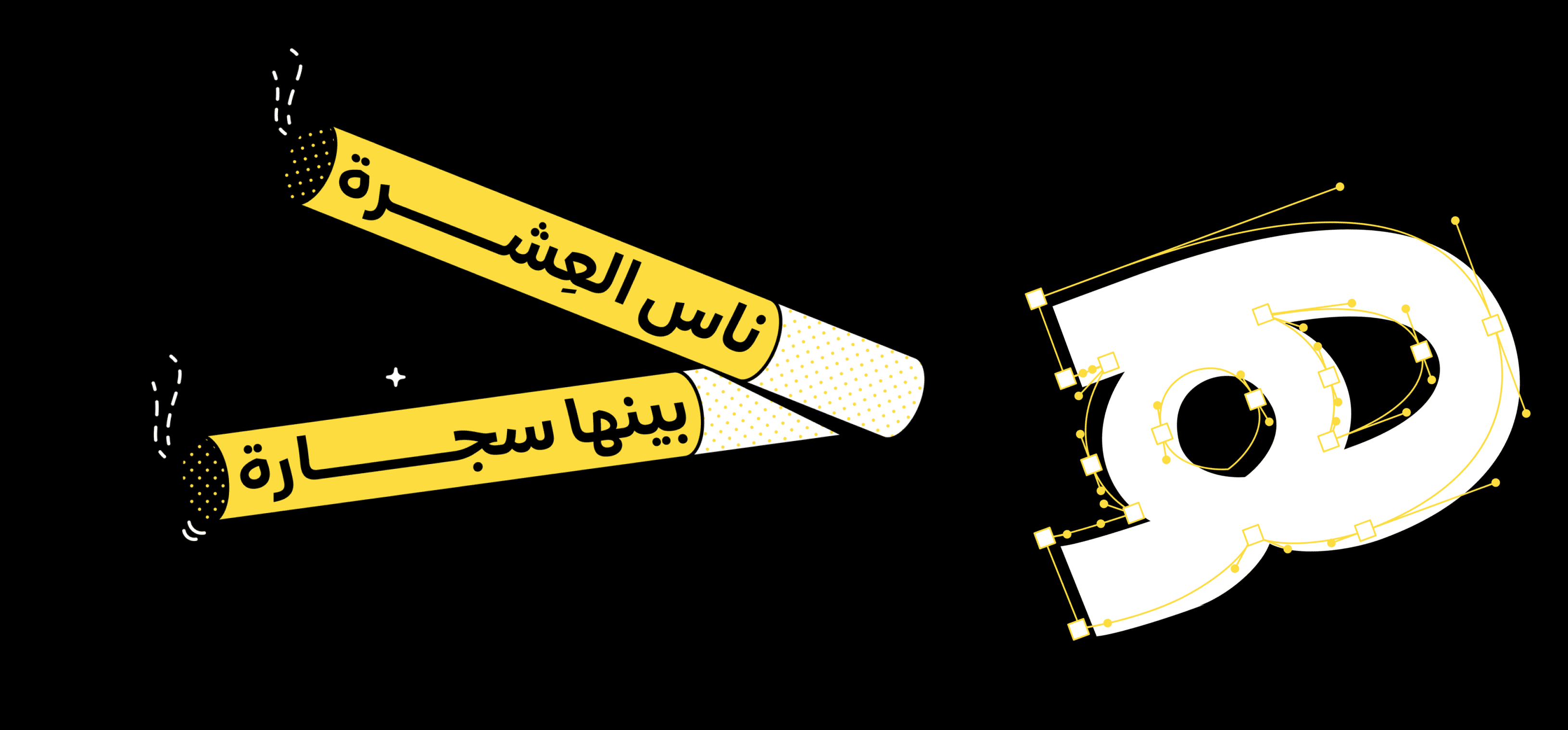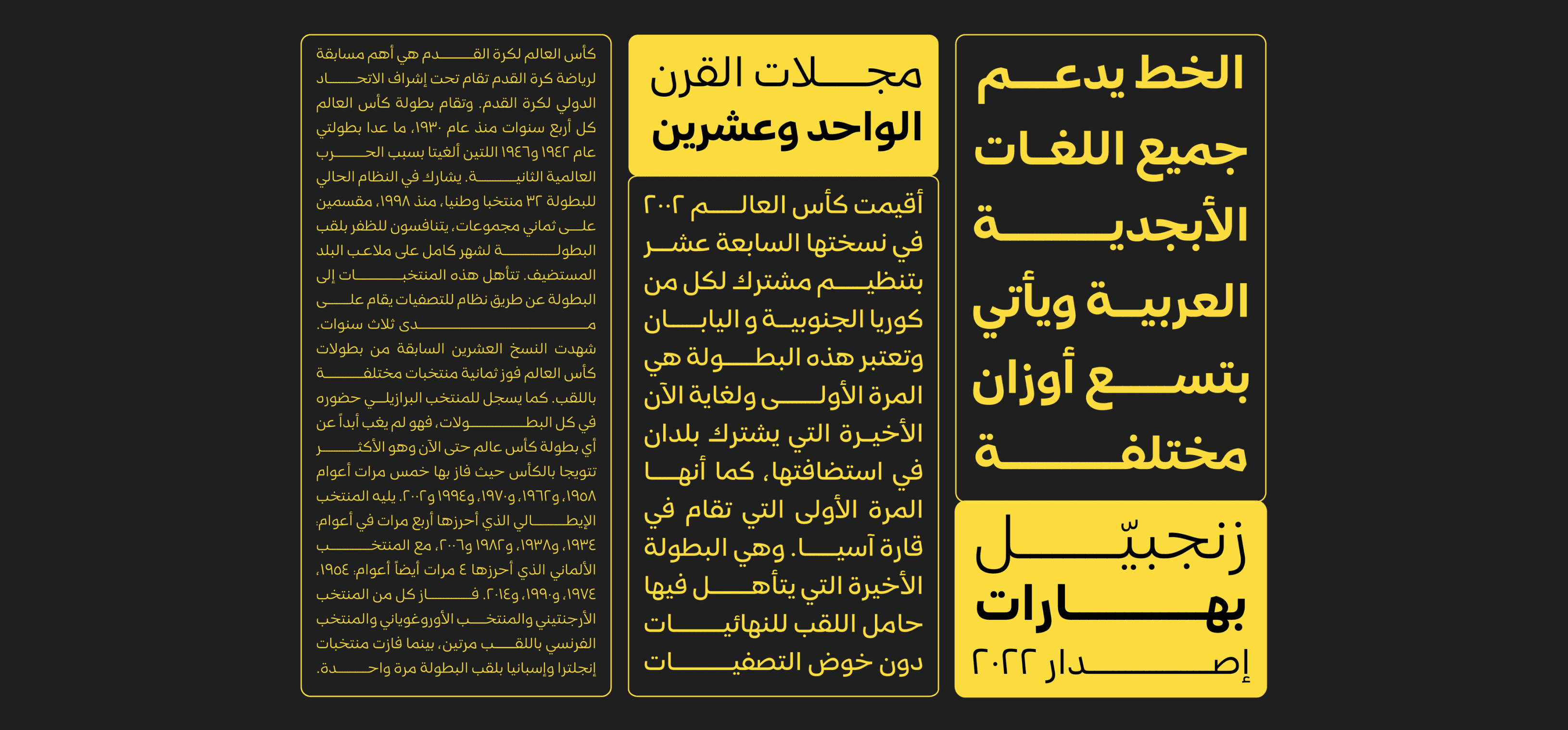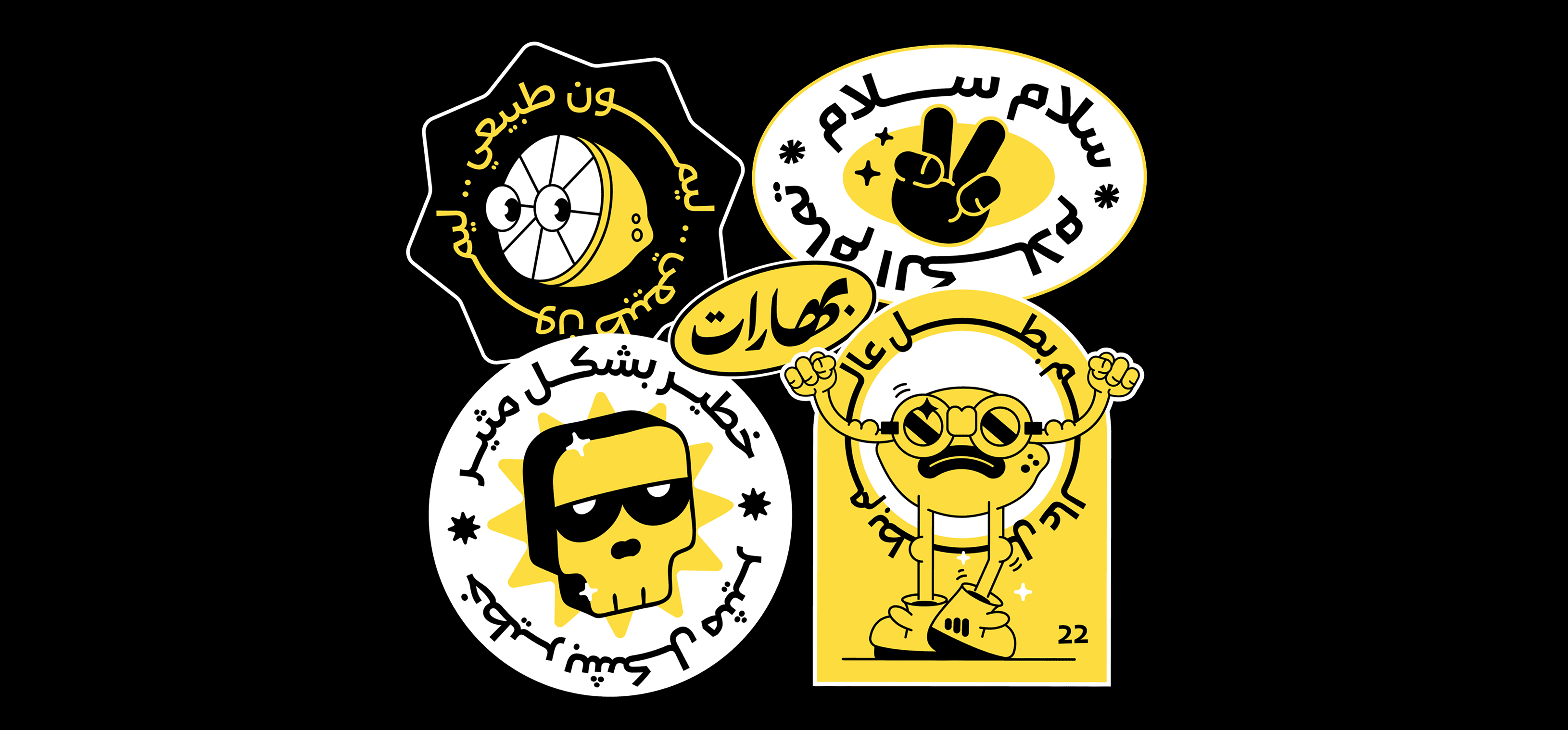
زنجبيل هو خط عربي بتصميم هجين يجمع بين أسلوبي النسخ والكوفي الحديث، ويأتي بتسعة أوزان متدرجة، مع بعض الحروف المائلة التي تضفي طابعًا فريدًا وحيويًا على النص.